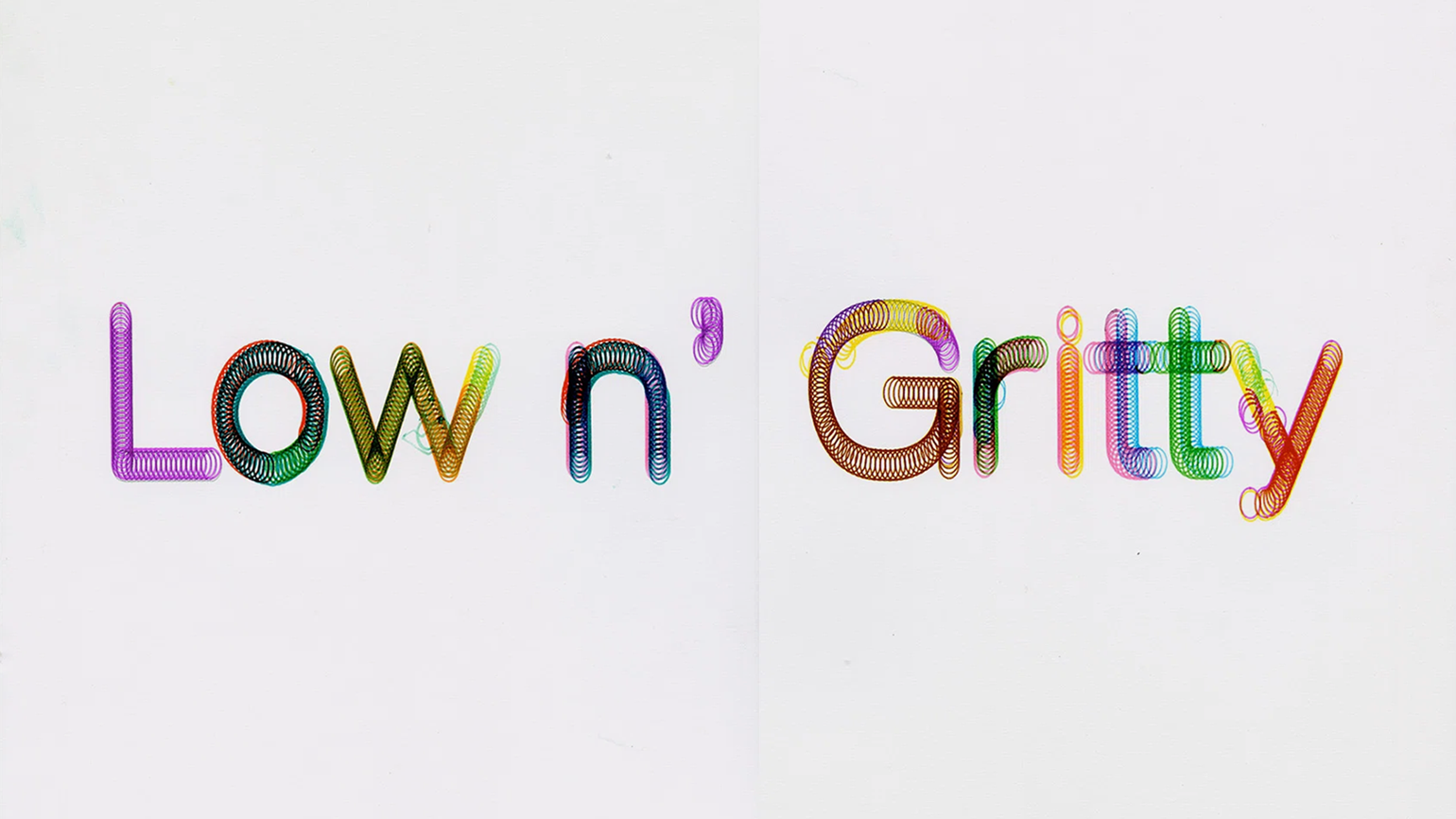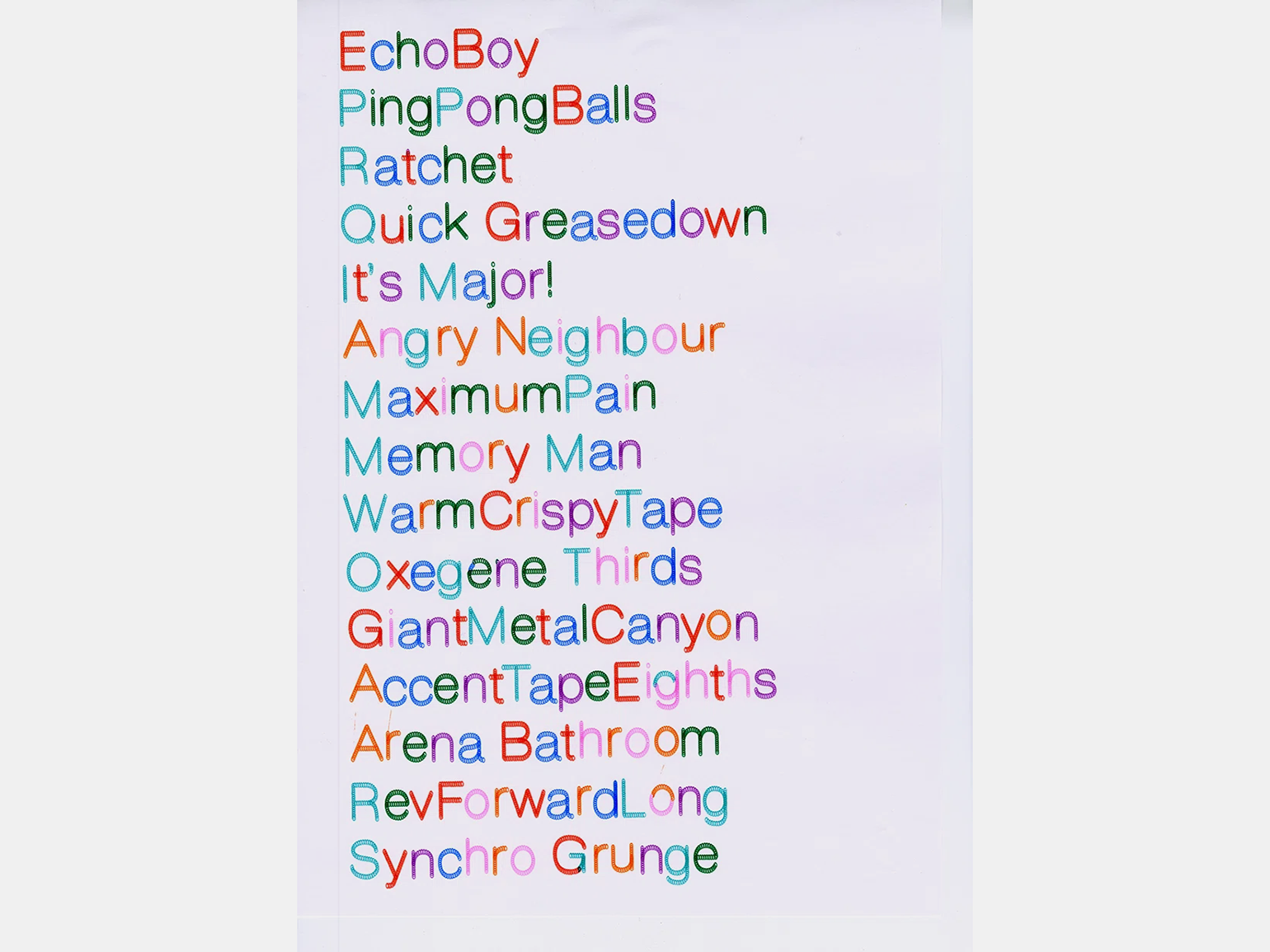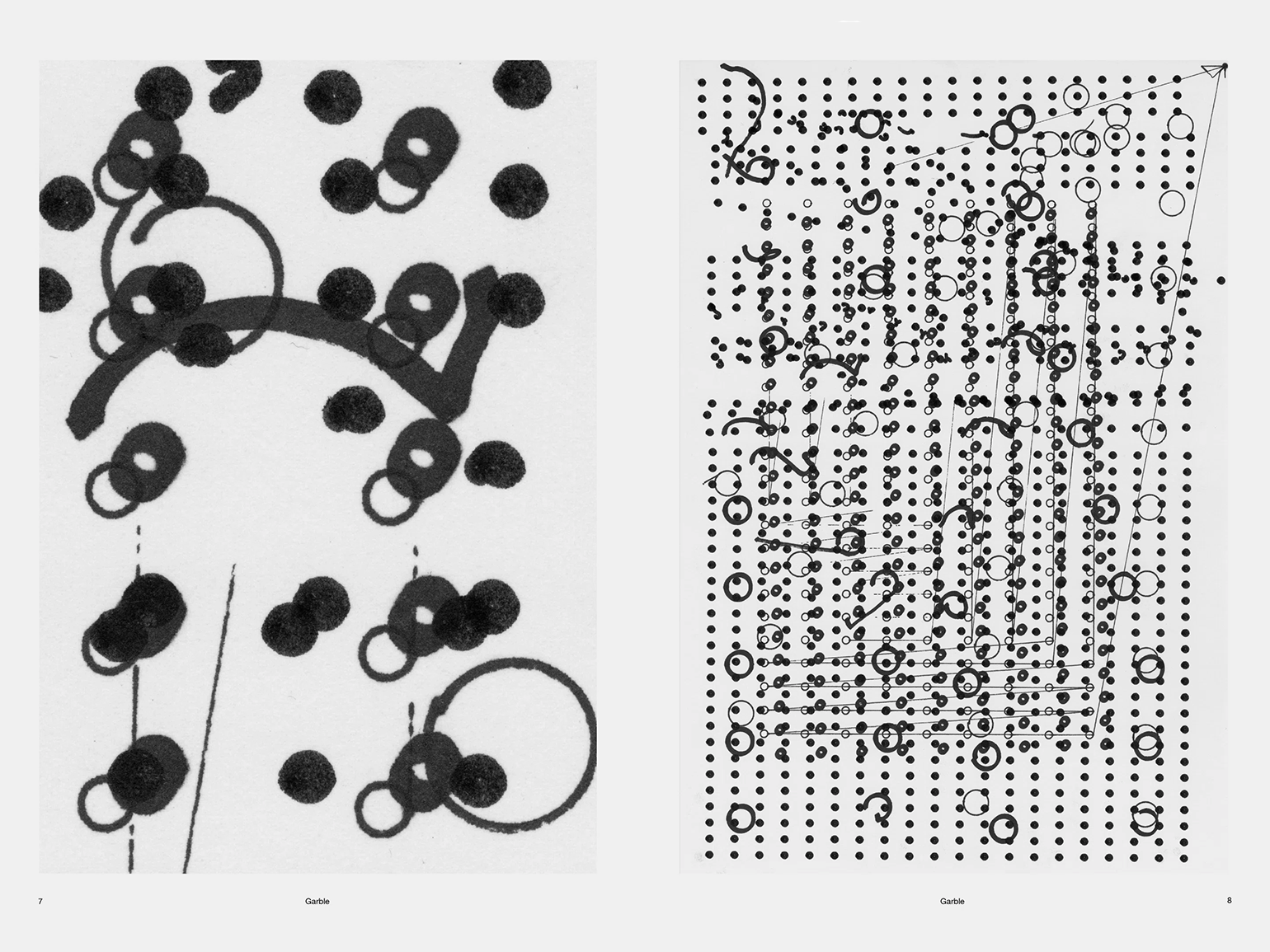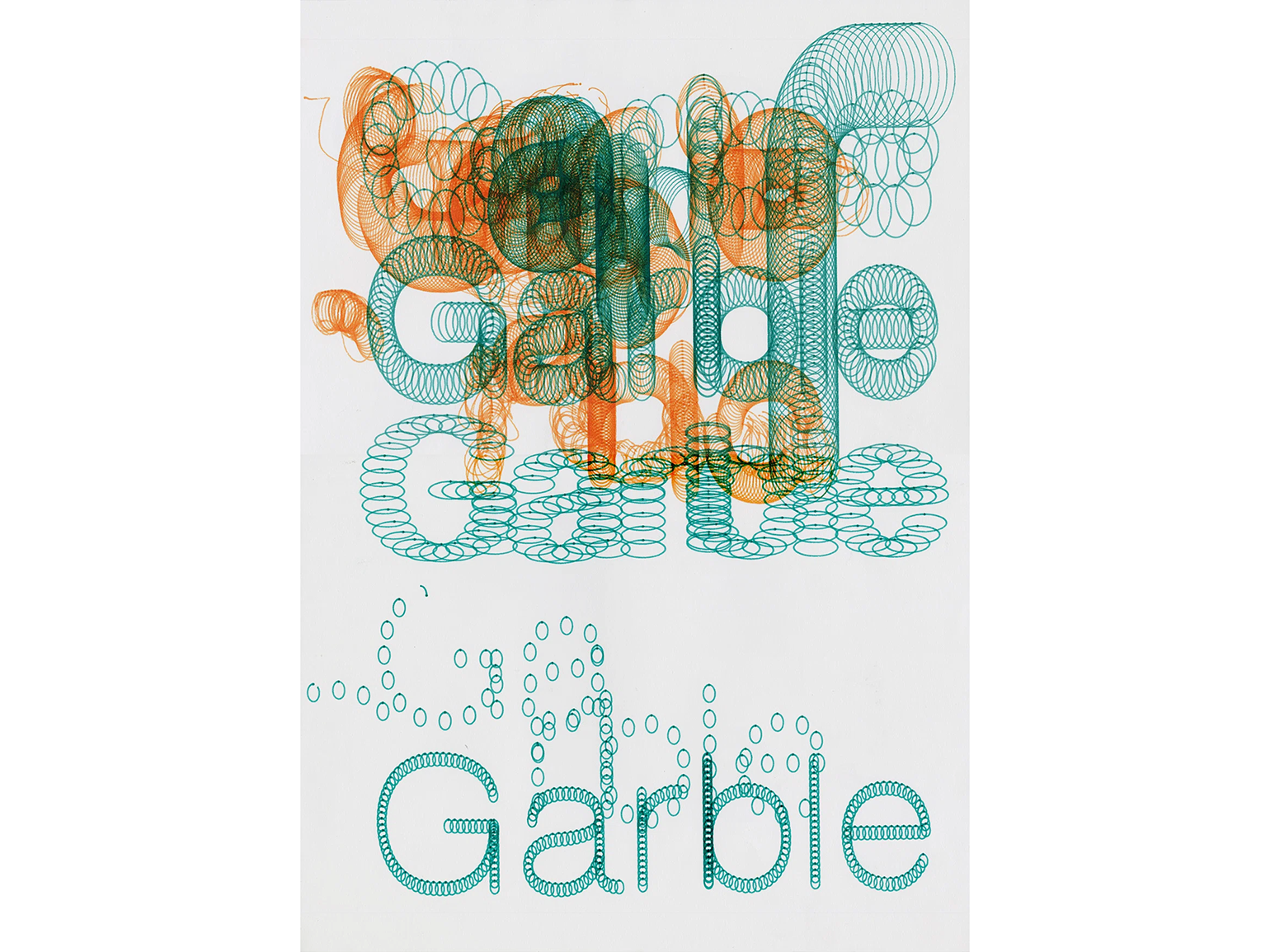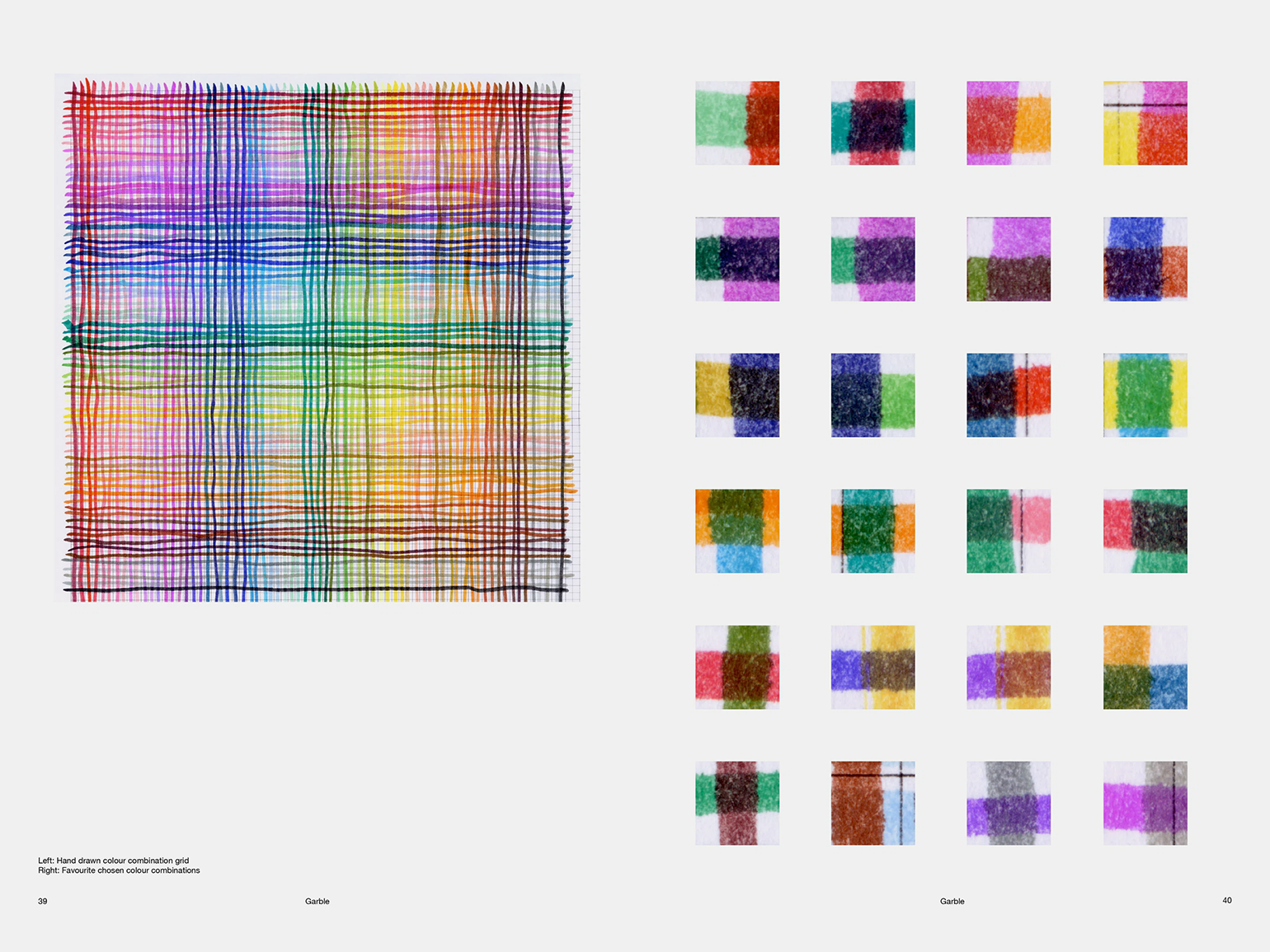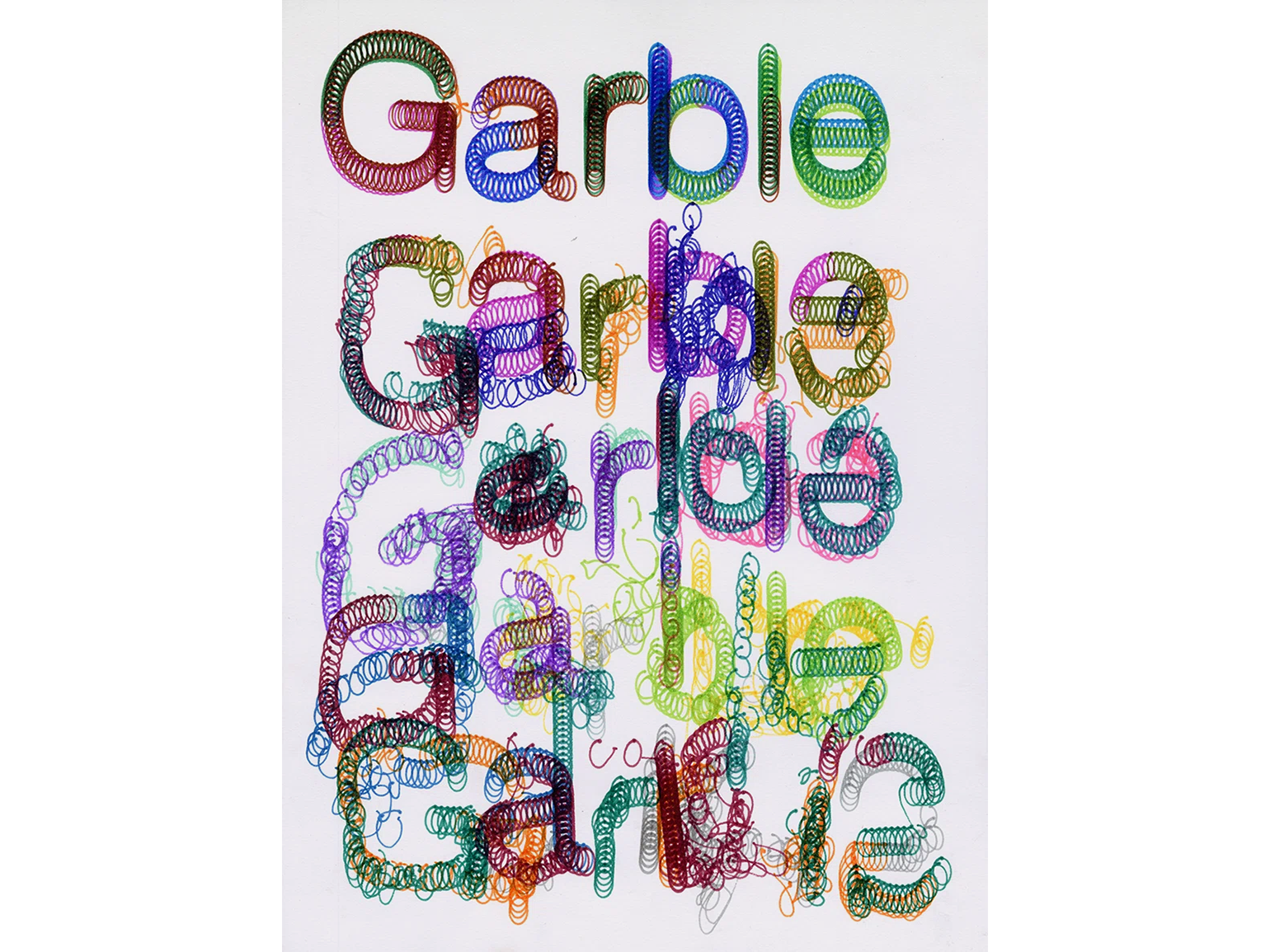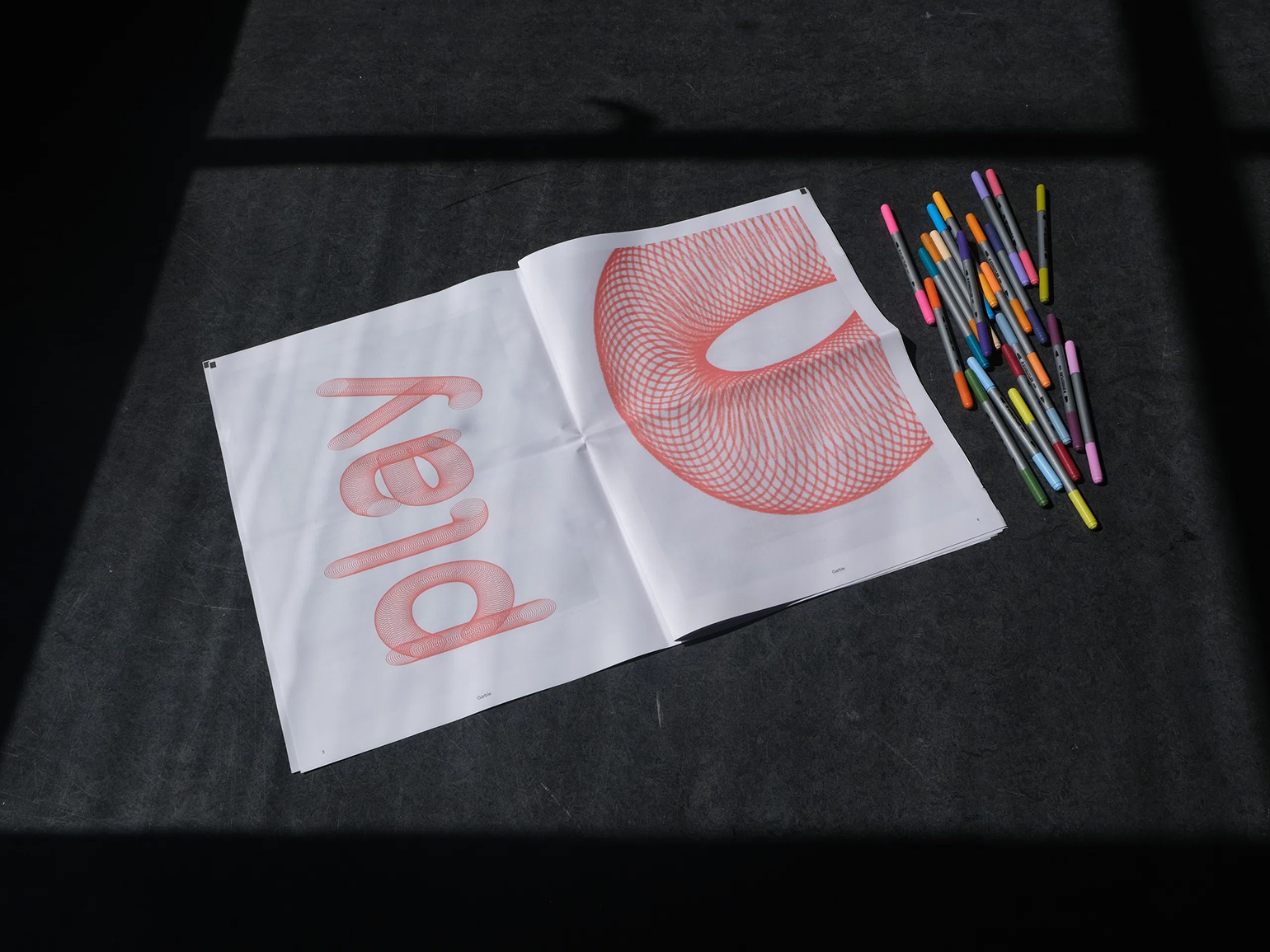
Дизайнер создал новый шрифт Garble, экспериментируя с плоттером
Итоговый результат во многом определило вмешательство автора в процесс.
Британский дизайнер Стэнли Плауман показал экспериментальный шрифт Garble и одноимённый зин. В этой работе он исследует границу между машинной точностью и человеческой непредсказуемостью. Проект создан с помощью перьевого плоттера — устройства, которое рисует изображения настоящими ручками и маркерами.
Идея Garble выросла из интереса Плаумана к традиционным инструментам для творчества и из воспоминаний о детских наборах для рисования — спирографах, трафаретах и фломастерах. Название проекта отсылает к видео о создании электронной музыки, в котором упомянут термин garble loops. По словам дизайнера, слово garble («неразбериха», «искажение») точно передавало экспериментальный характер работы.
В основе шрифта лежат контуры Helvetica, однако Плауман использовал их не как образцы для готовых символов, а как заготовку, позволяющую выстроить траекторию движения плоттера. По этим линиям машина наносила множество геометрических фигур, из-за чего буквы постепенно теряли привычную форму и превращались в сложные графические композиции.
Автор также экспериментировал с толщиной пера, расстоянием между элементами и размером рисунка, изучая ограничения технологии и возникающие в процессе визуальные эффекты.
Во время работы дизайнер решил отказаться от роли стороннего наблюдателя и начал вмешиваться в процесс. Он менял ручки, пока плоттер продолжал работать, сдвигал лист бумаги и накладывал несколько слоёв изображения друг на друга. Именно эти намеренные «ошибки», возникающие на стыке машинной точности и человеческой импровизации, стали главной идеей проекта.
По словам Плаумана, его особенно интересует сотрудничество человека и машины, а не попытка полностью автоматизировать творчество. В результате идеально выверенные окружности и линии, созданные плоттером, соседствуют с неожиданными смещениями, наложениями и разрывами, которые делают текст частично нечитаемым, но визуально выразительным.
Результаты экспериментов со шрифтом и процессом рисования собрали в отдельный зин.